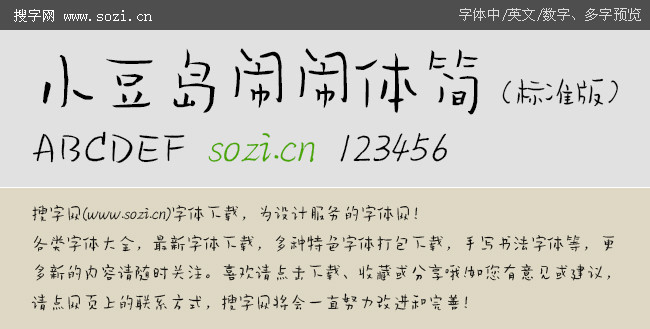
小豆島鬧鬧體簡(標準版)
搜字網(wǎng)給大家提供一款小豆島鬧鬧體簡(標準版)中文字體下載。小豆島鬧鬧體筆觸輕快隨性,筆畫輕重有度,字形靈動,形散神聚,落筆急促個性,整體給人以活潑跳躍的感覺,趣味十足。不對稱的字體形態(tài)在視覺上給人輕松感,極具手寫字體的個性風!適合兒童畫冊、兒童產(chǎn)品包裝設(shè)計、兒童類海報設(shè)計等應(yīng)用。(本字體為個人非商用版,如需要商用請聯(lián)系銳字家族購買版權(quán))